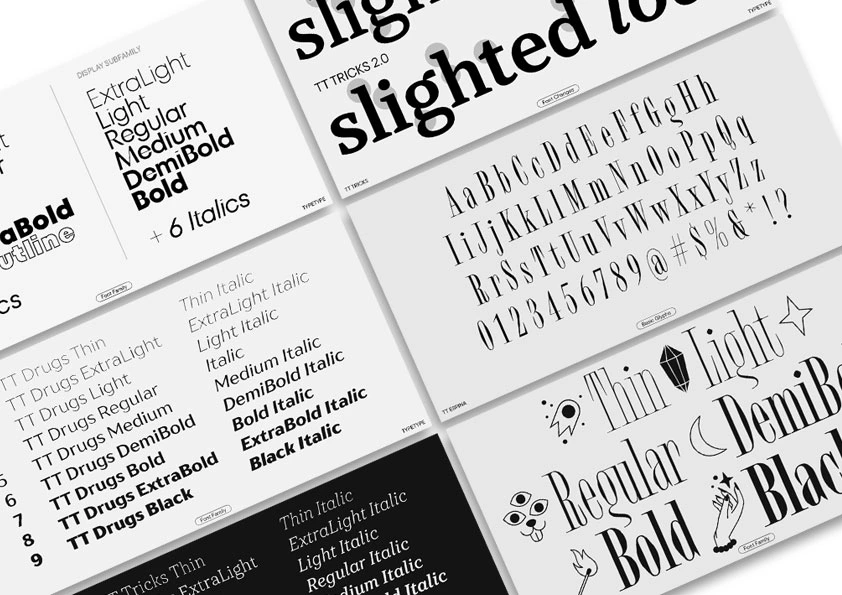
Fundición tipográfica Sobre TypeType
Creamos fuentes que inspiran
Nuestra misión es crear fuentes modernas, estéticamente agradables, multifuncionales y fáciles de usar, así como difundir conocimientos sobre diseño tipográfico. Estamos constantemente mejorando y monitoreando de cerca las tendencias para crear nuevos proyectos populares y actualizar los antiguos.
Acerca de la empresa
TypeType es un estudio de diseño tipográfico internacional, uno de los más grandes del mundo. Desarrollamos tipografías, brindamos servicios de personalización, masterización tipográfica (y otros).
Nuestras fuentes se utilizan por grandes empresas en todo el mundo, tales como Tom Tailor, Uniqlo, Cartoon Network, Telefónica, Mattel, Doordash, Vogue y otras.
Más de 80 empleados de diferentes países están trabajando en nuestros proyectos. El estudio cuenta con cinco departamentos: creativo, técnico, comercial, marketing y administrativo.
Para nosotros es importante apoyar y desarrollar el campo del diseño tipográfico, por eso participamos activamente en actividades educativas: publicamos regularmente artículos, podcasts, videos y otros materiales sobre diseño tipográfico, realizamos seminarios web, colaboramos con proyectos educativos y universidades, invitamos estudiantes a prácticas.
También ejercemos como socios en eventos de diseño.
Historia de la empresa
2013
Fundación de TypeType
2014
Lanzamiento de la primera fuente del estudio — TT Squares
2016
• Lanzamiento del primer curso educativo sobre el diseño de fuentes
• Inauguración de la oficina
• Nuevo enfoque a la creación de fuentes: ampliamos los caracteres y variantes de escrituras, introducimos OpenType
• Lanzamiento de la primera fuente creada en el nuevo enfoque — TT Lakes
2017
• Lanzamiento del más vendido — TT Norms
• Creación del departamento técnico. Mejora de calidad de las fuentes.
2018
Lanzamiento del segundo más vendido — TT Commons
2019
Empezamos a trabajar con las grandes marcas
2021
• Apertura de la oficina en EE. UU.
• Ampliamos el número de empleados hasta 30+
• Nuevos servicios: customización, desarrollo de escrituras personalizadas para las grandes marcas, mastering y hinting
2022
Apertura de la oficina en Kazajistán
2023
• Inauguración de nuestra tienda en línea
• Apertura de la oficina en EAU
• Primer meet-up de TypeType
2024
• Premio Red Dot: Best of the Best
• Socios con Granshan y ADCR
2025
• Desarrollo de las fuentes más populares: lanzamiento de idiomas basados en el alfabeto árabe
• Lanzamiento del laboratorio creativo «TT Labs»
Sobre las fuentes
La colección TypeType incluye más de 75 tipos de letra comerciales de varios tipos: decorativas y textuales, sans serif y serif, manuscrita y slab, contorno y monoespacio. Muchos de ellos contienen fuentes variables que el usuario puede personalizar de forma independiente según uno o más parámetros (ancho, negrita, inclinación).
Todas nuestras fuentes se actualizan y constantemente para que cumplan con los requisitos técnicos y estéticos modernos. Incluyen un conjunto funcional de funciones OpenType y un amplio soporte de idiomas (en particular, una gran cantidad de idiomas basados ​​​​en el alfabeto cirílico).
Los más vendidos del estudio incluyen 7 tipos de letra: TT Norms® Pro, TT Commons™ Pro, TT Fors, TT Firs Neue, TT Hoves Pro, TT Interphases Pro, TT Ramillas.
Las fuentes TypeType ganan regularmente premios en importantes concursos internacionales como Red Dot, Granshan, Muse, Workspace, Indigo y otros.